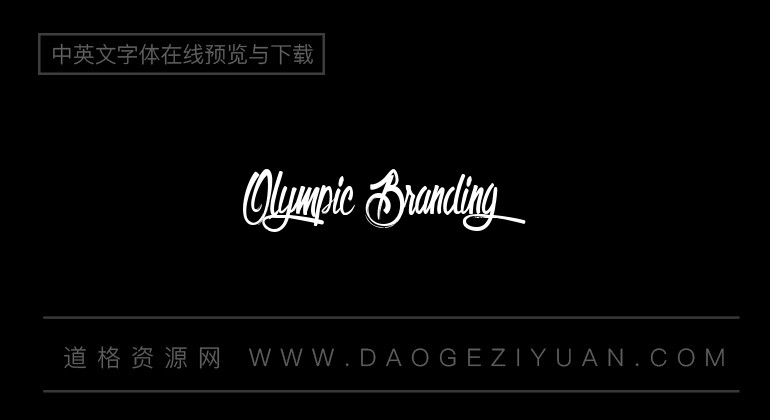
Olympic Branding
Olympic Branding 字体是一款具有现代感的字体,它主要用于品牌标识、宣传印刷品和网页设计等。这款字体以简洁、立体、动感的特点赢得了广泛的赞誉。它的字体设计灵感来自于奥林匹克运动会的品牌形象,以及传统的商业标识设计。它的字形设计具有良好的可读性,可以提供清晰的文字表达,而且还具有良好的美学效果。Olympic Branding 字体可以提供多种字体样式,包括细体、粗体、斜体等,可以满足不同的设计需求。
Olympic Branding是一款非常不错的手写艺术字体,具有很好的视觉感,适合于文化类的宣传设计、商业类品牌的广告和产品包装设计以及个性化文字排版等较多场景。